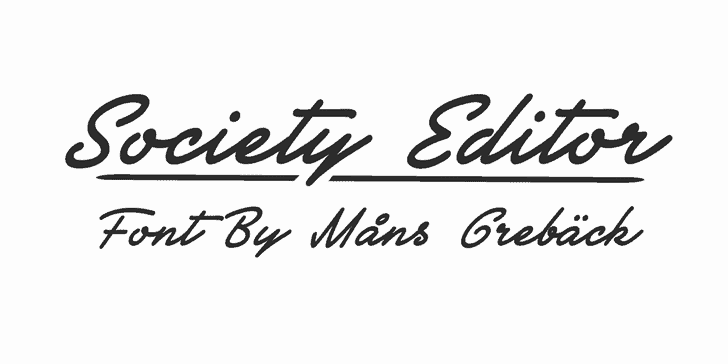
Society Editor font
A fonte Society Editor é uma escolha perfeita para aqueles que procuram um script fluido e envolvente. Desenvolvida pelo designer Hamilton, ela oferece linhas elegantes e curvas suaves que criam um impacto visual único em qualquer projeto gráfico. Essa fonte Script se destaca por suas habilidades de personalização, permitindo uma variedade de aplicações em logotipos, headlines, textos longos e até mesmo design editorial. Para os designers interessados em obter uma licença comercial para usar a Society Editor em seus trabalhos comerciais, visite o site oficial da MansGreback.com/society-editor. Perfeita tanto para trabalho pessoal quanto para projetos profissionais, esta fonte é um investimento que vale a pena. Eles podem ser utilizados em qualquer formato de mídia digital ou impressa e garantem uma experiência visual diferenciada em seus trabalhos. Com a Society Editor na sua coleção, você certamente impressionará suas clientes e leitores com seu estilo singular e sofisticado.